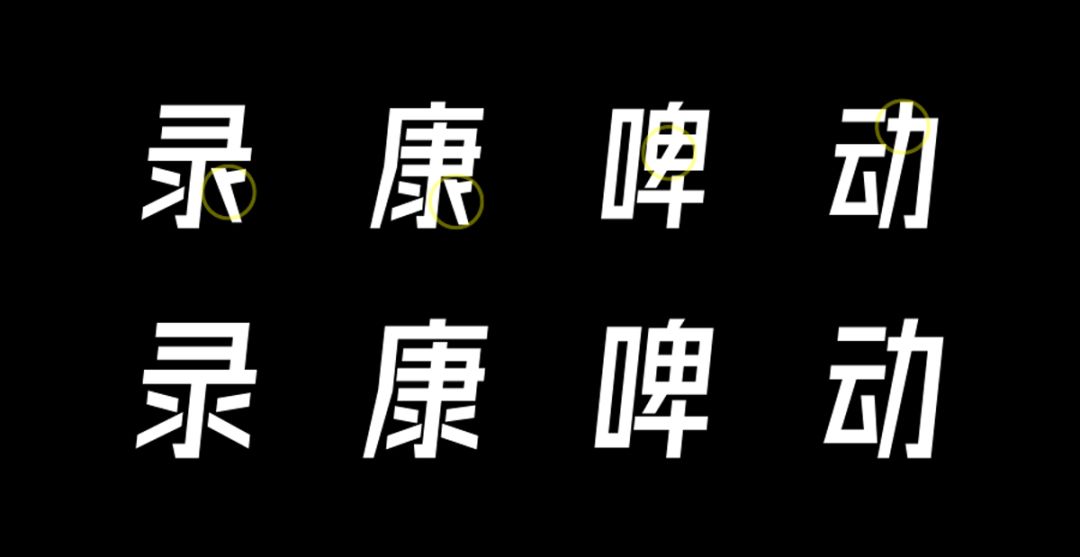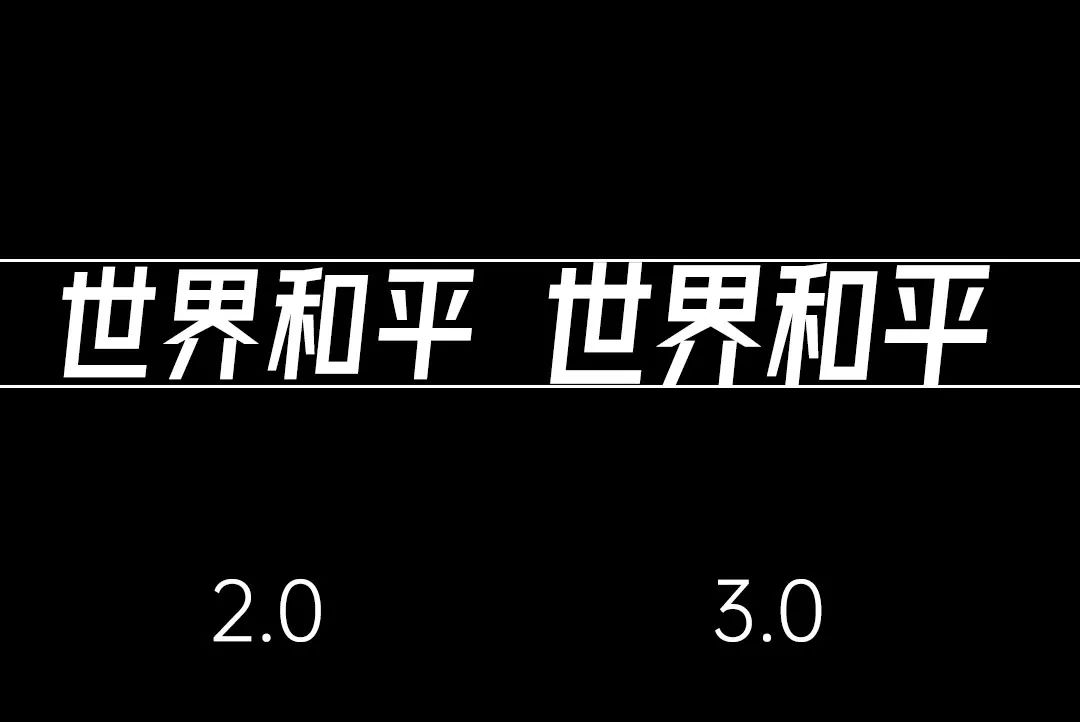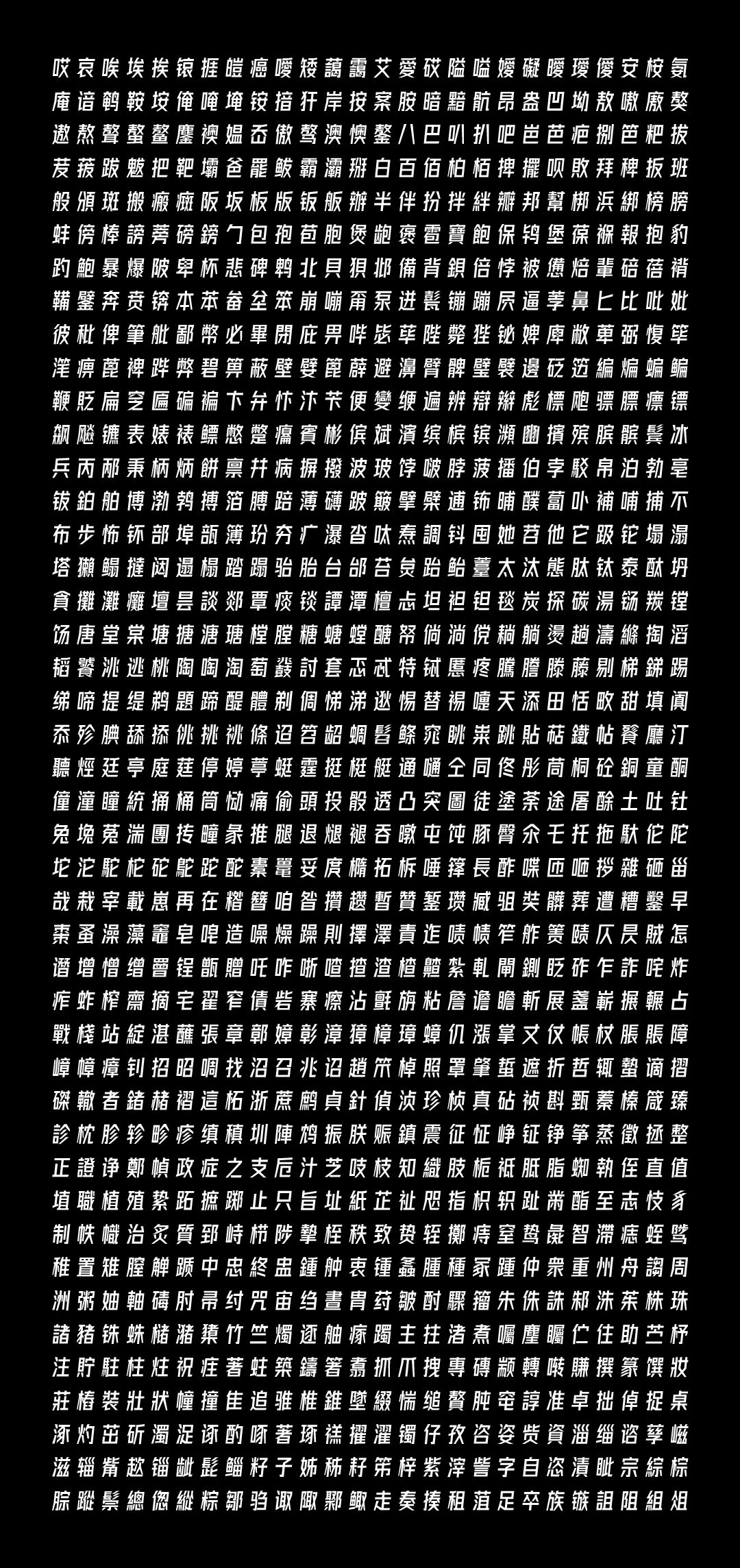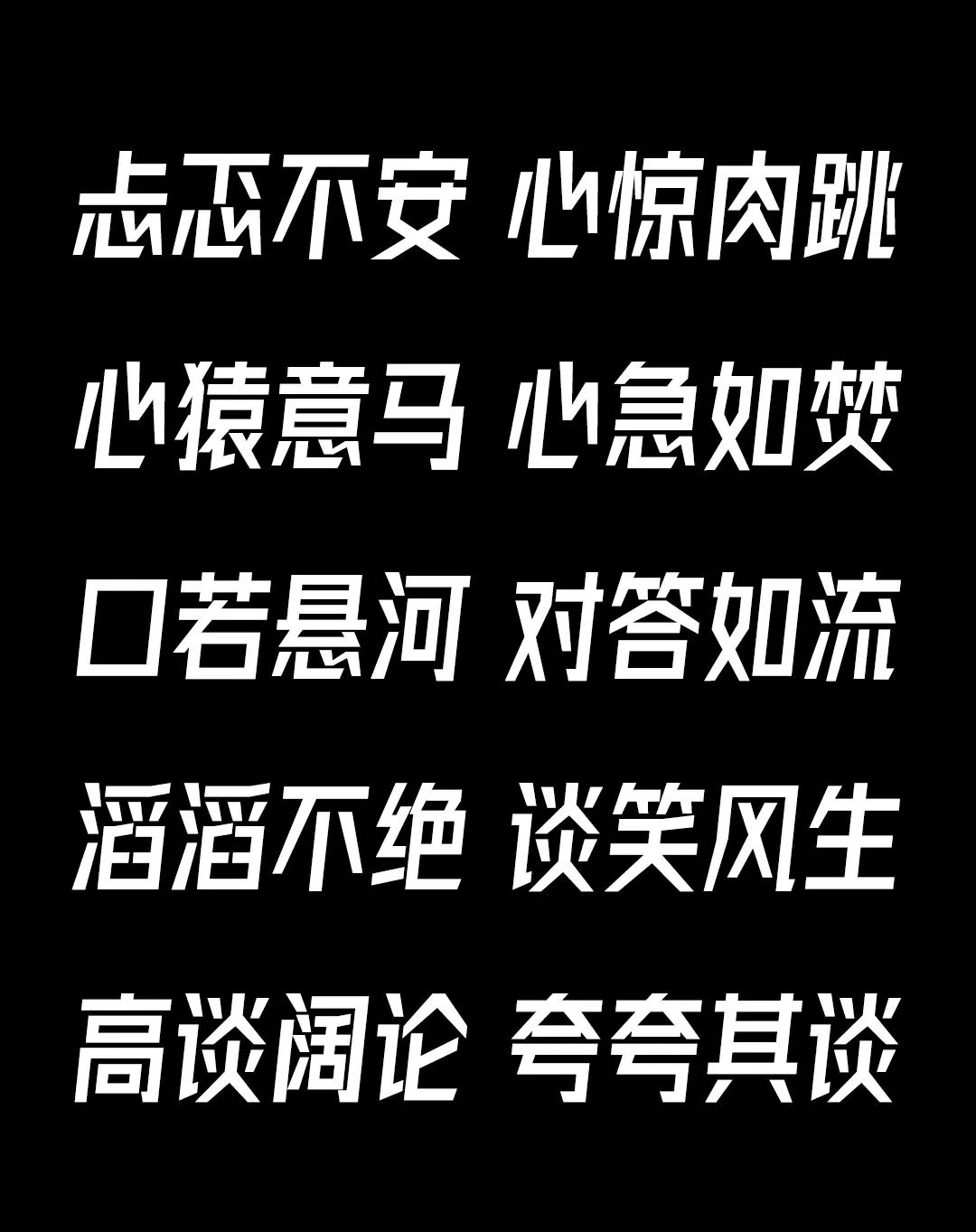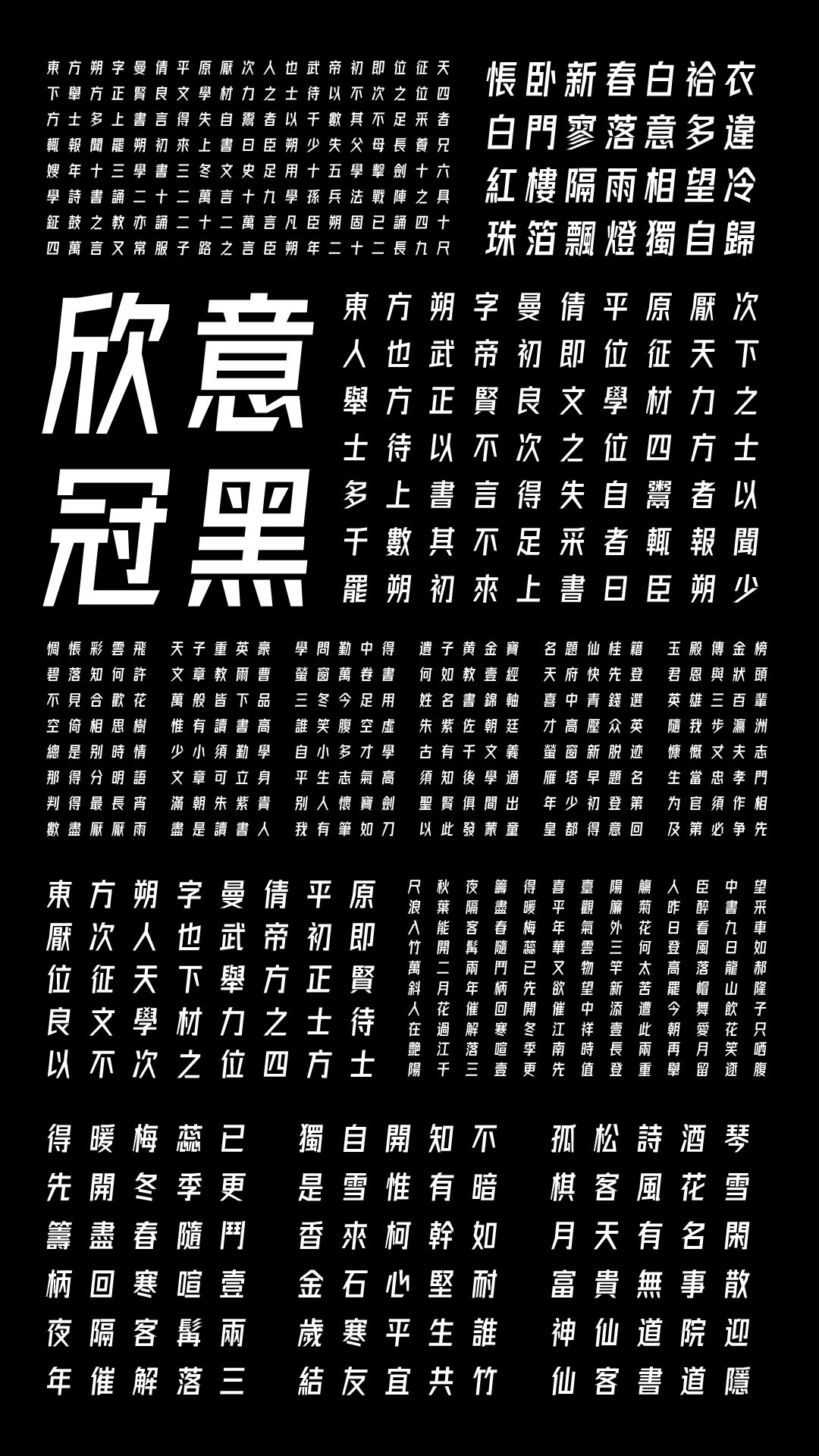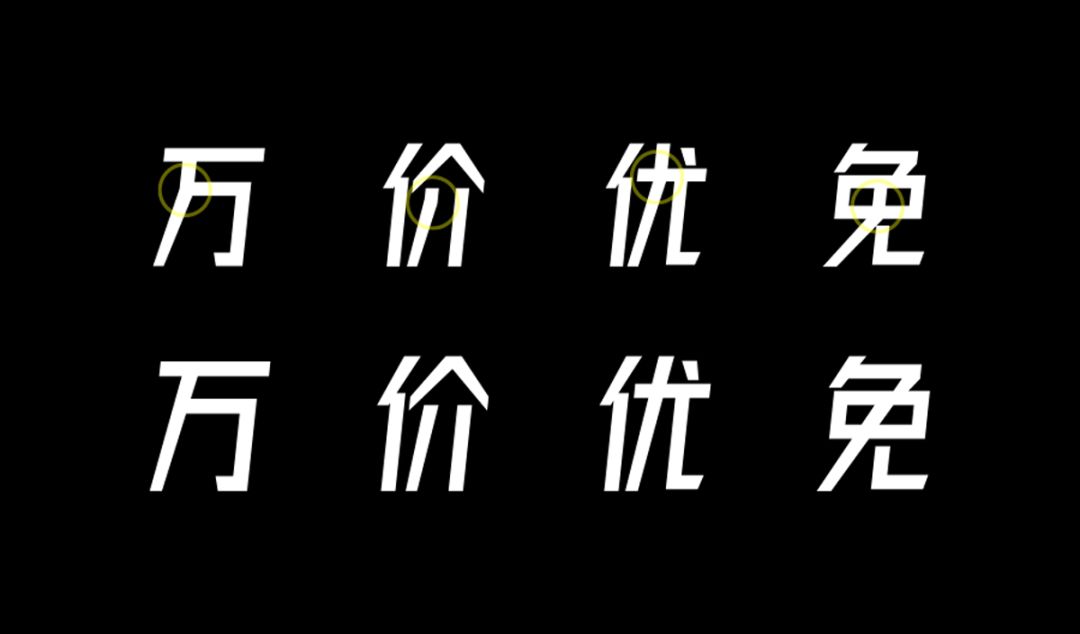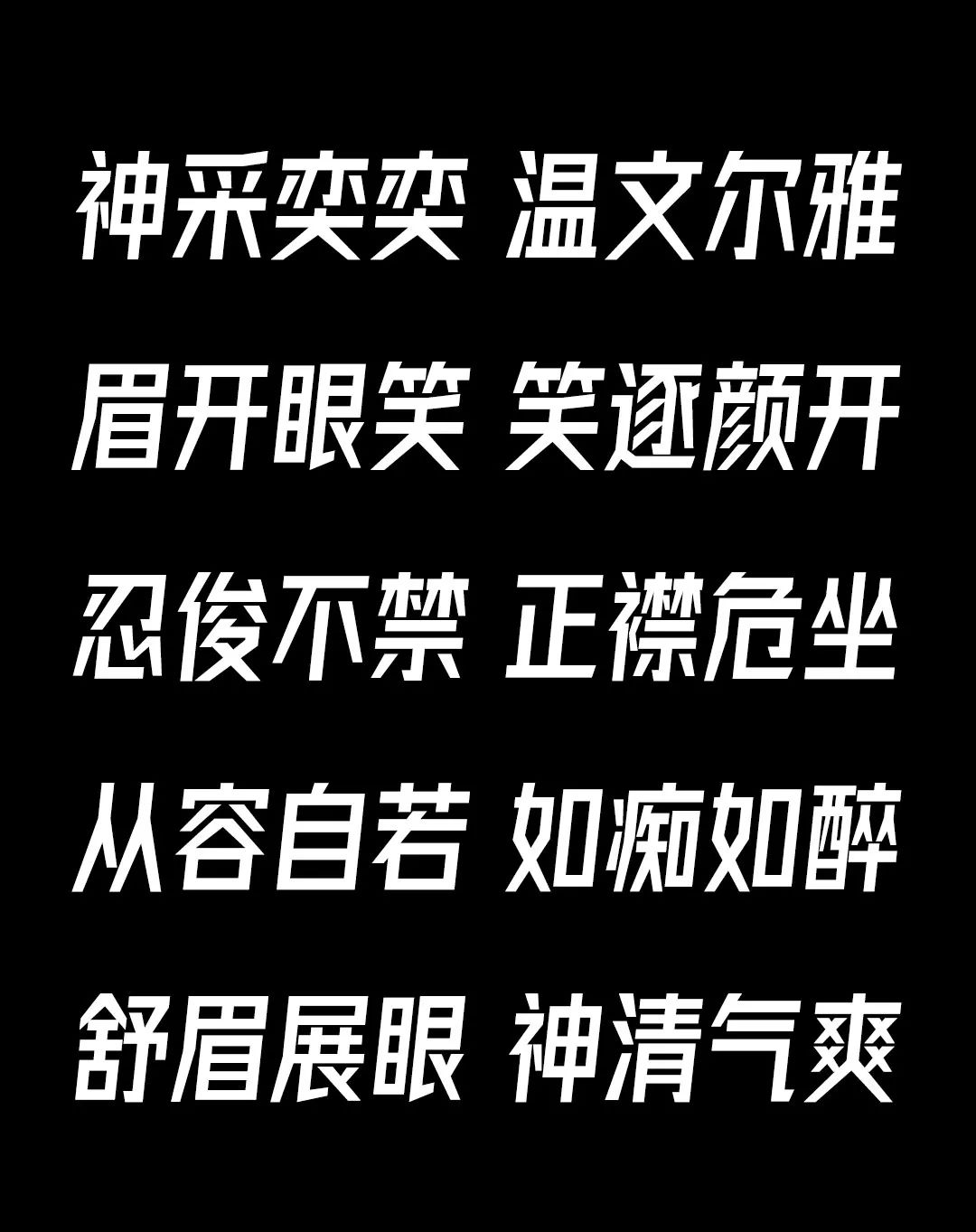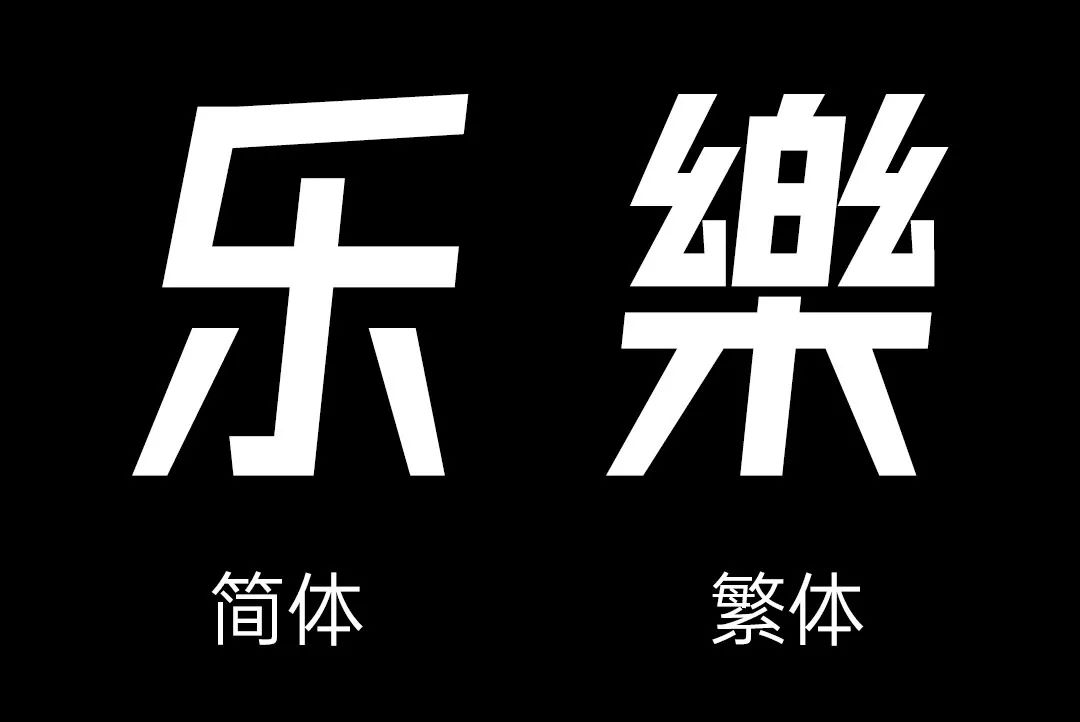
今年4月1日我发布了第一套字,也面临了很多问题,仅半个月就更新了2.0版本,当时夸下海口说不出意外3.0就是繁体版,同时也有不少的朋友跟我反应这个字的各种各样的问题,当然当时也把这些问题都解决了,重心还是在繁体设计上面。但你看完今天的文章,你会惊奇的发现,今天所更新的内容更加实用!
字体圈欣意系列公益字体都将会对面向全社会全媒体免费商用的。
全新3.0更新了什么?
1:更改部分字形设计
2:重新设计西文数字标点部分
3:添加3000+个繁体字符,现在字符数量是将近10000个了
4:还原字形默认大小
5:添加了生僻字“biang”
添加3000+个繁体字符
繁体部分是这次更新的重心,前前后后白天也弄晚上也弄,也花了四个月的时间。中文现涵盖9169字,另按需添加若干生僻字,56个英文10个数字,标点若干。虽然增加繁体只有三千多字,比简体少了整整一半,但是做起来比简体复杂得多,很多字的笔画非常多,甚至比简体多好几倍,所以工作量并没有想象中相应的减少。
例如你看下面:
由上可以看出,简体比繁体轻松多了!这也就是为什么市场上这类的免费字库,都是只有简体版本的原因,经济损失更大,花费时间多,实际使用的人不多。
更改部分字形设计
有些字形过于花哨,当时觉得这样OK了,但是后面做繁体的时候,越看越不顺眼,觉得为什么当初设计的时候要要这样处理,现在看真丑,调整优化了之后好很多了。
重新设计西文
英文部分真的是这套字的诟病,经常看到用我的字的例子,还得自行去调整英文数字,甚至直接换了别的英文字体替代,所以我就直接把英文部分全部重新设计了,另外也把字面高以及风格调整的跟中文更匹配了,真的是英文字符虽然少,但是需要考究的方面还真不少。
还原默认字体大小
当时刚发布更新2.0的时候,就有留言说字体变小了,才发现真的是比1.0小了很多,既然有问题那必须解决!
添加生僻字“biang”
这个彩蛋小惊喜,其实这个字在朋友圈我已经发过了哈哈,我应该是全球首个免费字库里做这个字的了吧!!如果在我之前别的免费字库中有做了,当我没看见。目前专门针对这个字进行设计的字库是很少的,并且汉字里没有对这个字的编码,但他可以说是生僻字中的佼佼者,不比其他生僻字用的少,尤其在陕西。算是一次新的尝试吧,讲真这一个字,搞了半小时抠细节,哈哈哈。(之,穴,月,幺,言,幺,長,馬,長,刂,心)